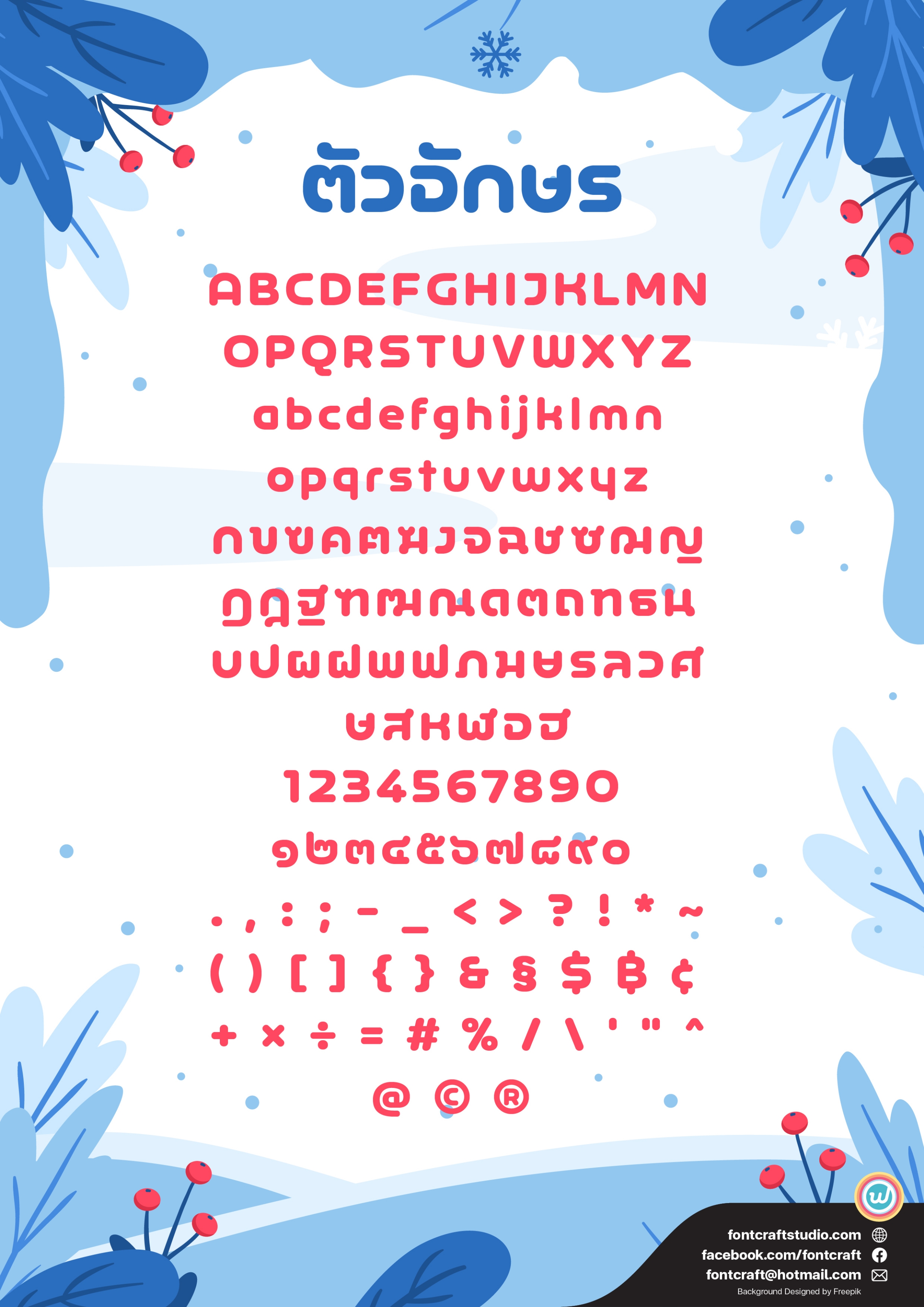
เอฟซี อิกลู ราวด์ (FC Igloo Rounded)
ฟอนต์เอฟซี อิกลู (FC Igloo Rounded)
แบบตัวมนของฟอนต์ เอฟซี อิกลู เพิ่มความนุ่มนวลชวนอ่านมากยิ่งขึ้น
เมื่อหนึ่งรูปทรงถูกยกขึ้นมาเป็นโจทย์ให้ออกแบบตัวอักษรที่เข้ากันกับทรงโดมบ้านอิกลู และยังคงเข้ากันกับตัวอักษรอื่นๆ ด้วย
จึงเกิดเป็นฟอนต์ที่แปลกตา แต่ก็เข้ากันได้อย่างน่าแปลกใจ
ฟอนต์เอฟซี อิกลู ราวด์ (FC Igloo Rounded) คู่แฝดของฟอนต์เอฟซี อิกลู